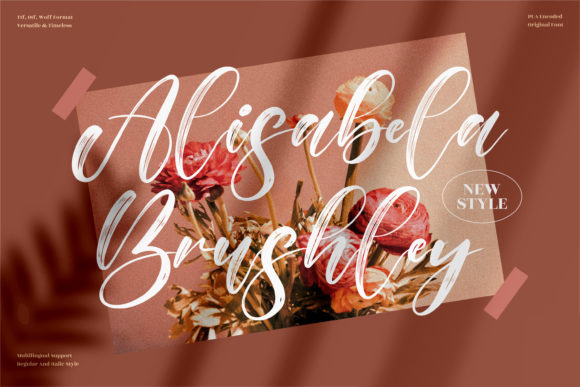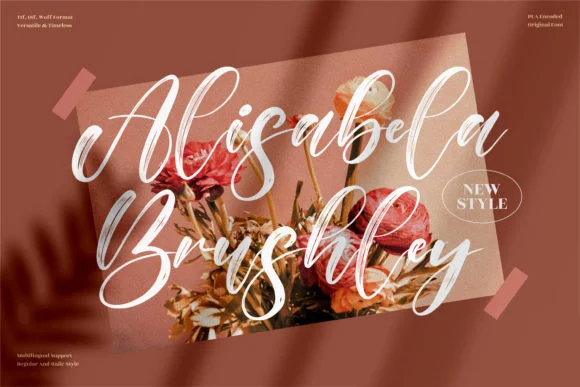
Название: Alisabela Brushley Font (2021)
Alisabela Brushley - это стильный и матовый шрифт.
Влюбитесь в его восхитительный стиль и используйте его для создания великолепных свадебных приглашений, красивых канцелярских принадлежностей, привлекательных постов в социальных сетях и многого другого!